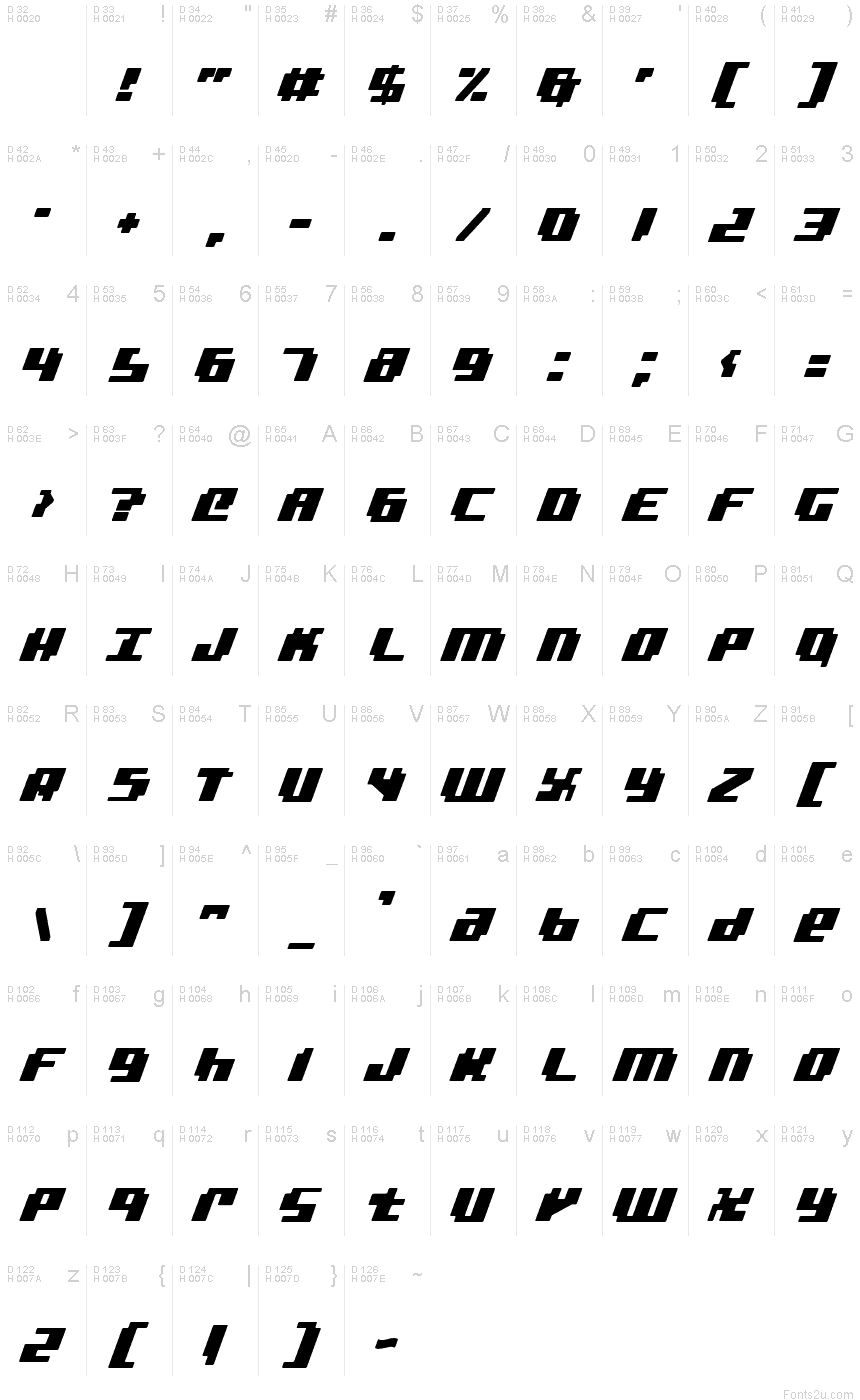
Bad Robot Italic od Iconian Fonts to darmowy, futurystyczny font cyfrowy o niskim, szybkim rytmie. Litery są pochylone do przodu i mają masywne, zazębiające się kształty, a ścięte rogi oraz szerokie pociągnięcia nadają całości mechaniczny, sci-fi charakter, który nie wydaje się sterylny.
Font naturalnie sprawdza się w logo gier, nagłówkach plakatów, okładkach mixtape'ów, kartach tytułowych i brandingu technologicznym, wszędzie tam, gdzie darmowy font potrzebuje silnego efektu ruchu. Dzięki kompaktowej i spójnej formie, świetnie nadaje się również do krótkich nazw na opakowaniach, grafik dla streamerów oraz elementów interfejsu, które mają mieć surowy, syntetyczny wygląd.